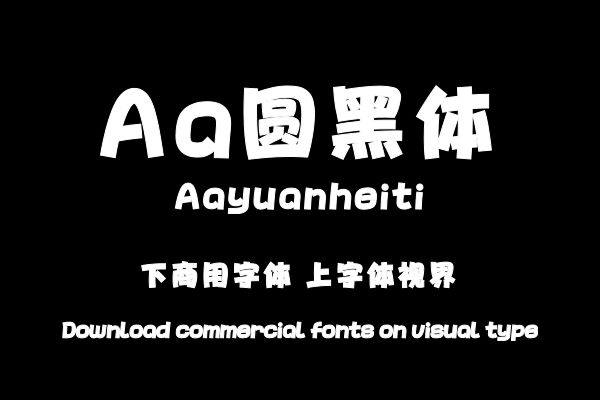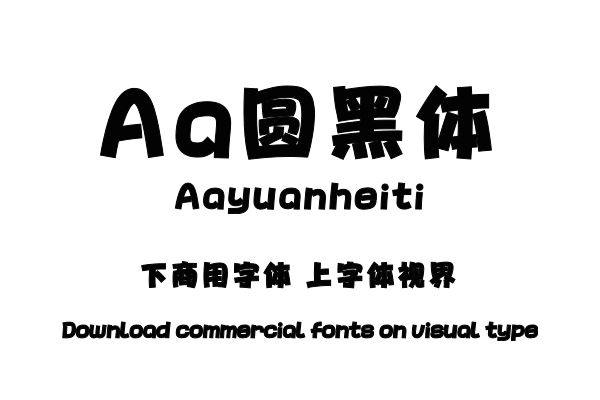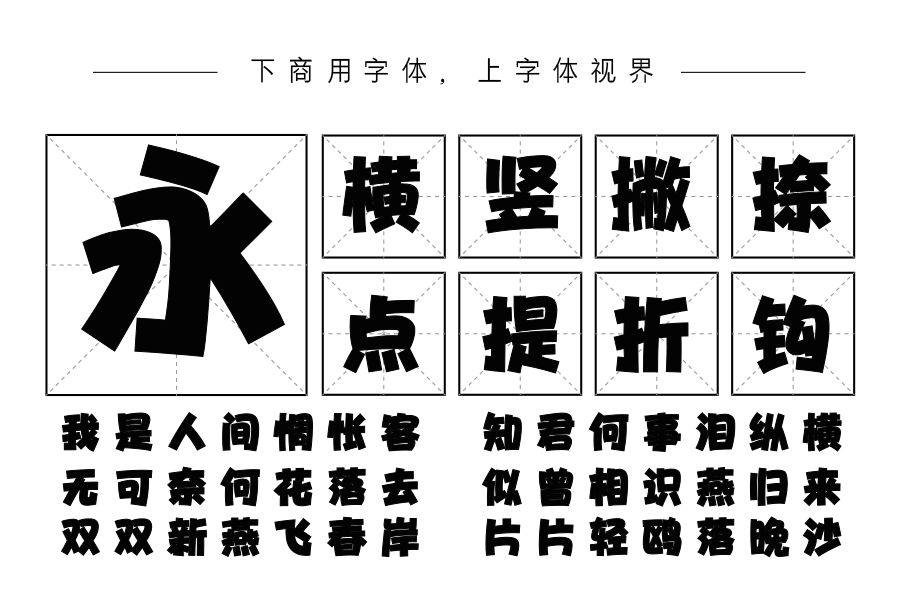
一款具有手绘POP风格的创意字体。笔画模拟马克笔的书写形态,非水平和垂直,略有弧度,折笔处呈圆形。圆黑体笔形棱角分明,风格活泼俏皮,适用于商场和网店的促销广告,......购买须知:“下载服务费”与“字体VIP”所获得字体 仅用于个人非商用, 商用请联系付费授权。本字体为电脑用字,手机没有root权限不支持直接手机换字(手机如何root,请自行百度搜索教程)。购买前请先 了解清楚后再付款 ,字体为虚拟产品无法回收 一旦购买不支持退款。